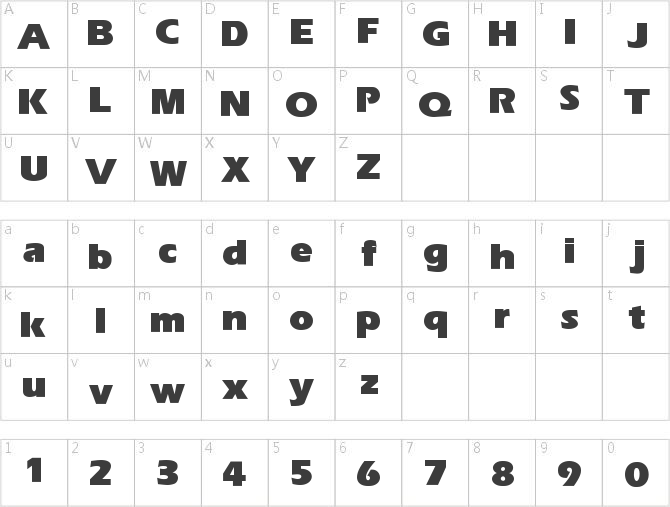
Eras-UltraBlk-Heavy(1) 詳情頁
Eras-UltraBlk-Heavy(1)字體字庫是一款讓人賞心悅目、百看不厭的英文字體,適合各類廣告和產(chǎn)品包裝設(shè)計應(yīng)用,字體大小0.03MB,格式為ttf字體,上傳用戶是浪跡天涯,作者/版權(quán)方為未知